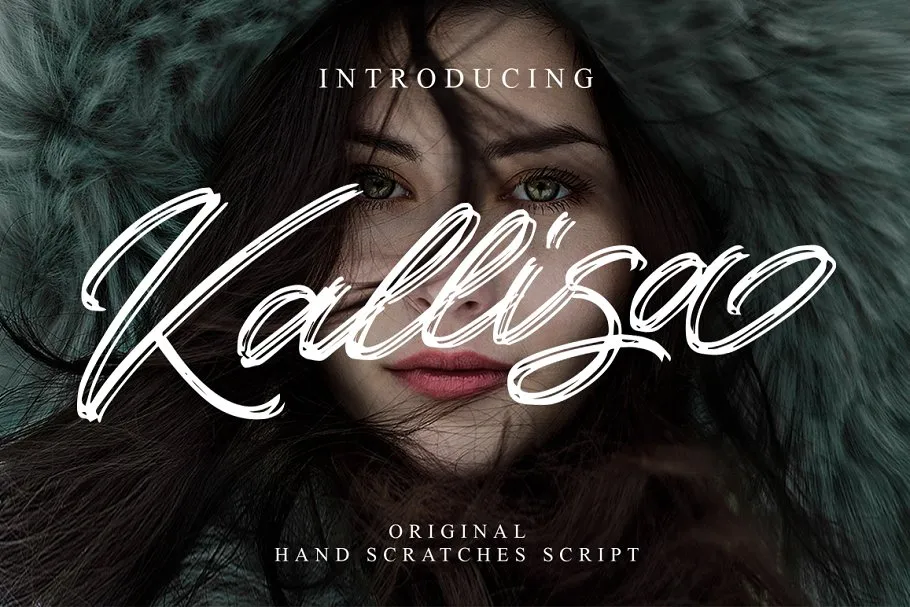
Kallisa Script Font
Kallisa Script Font é uma fonte moderna criada pelo designer independente 24Design. Desenvolvida no estilo de letra aquarela, essa fonte apresenta nuances únicas e autênticas do pincel que realçam sua versatilidade. Ideal para um vasto leque de projetos, desde o layout da loja virtual até as cartas de casamento ou o design gráfico, Kallisa Script é uma escolha perfeita para dar vida a suas criações. Seus traços fluidos e suaves capturam nuances do mundo real que podem ser úteis em qualquer aplicação visual criativa. Seja você designer gráfico, blogger, artista de moda ou até mesmo um entusiasta da arte digital, Kallisa Script é uma fonte script de qualidade para todos os seus projetos digitais.